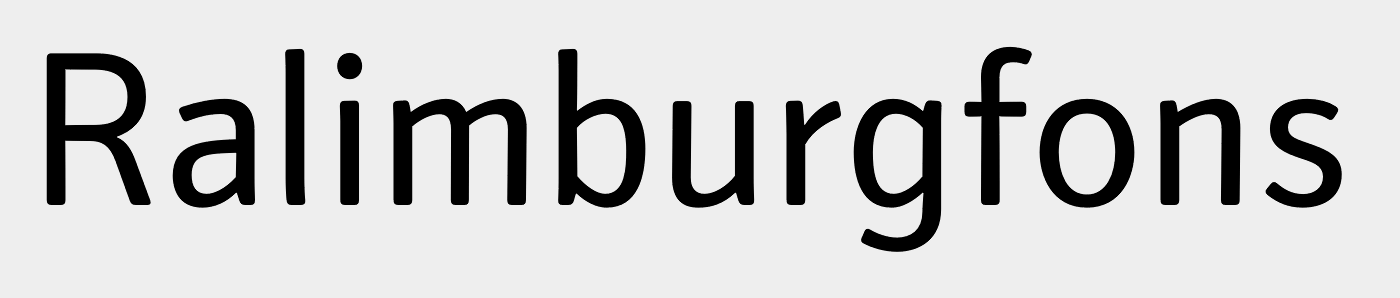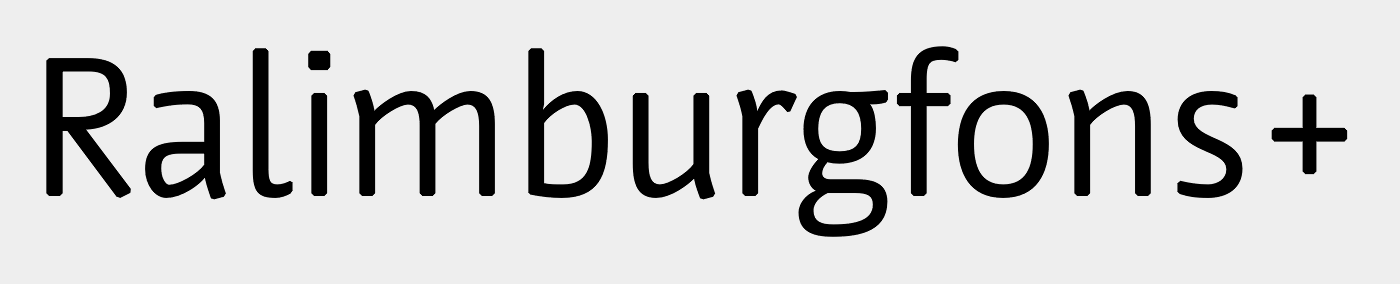
Schriften mit abgerundeten Ecken - Alternative zu Amsi Pro
Ich bin auf der Suche nach einer Schrift mit abgerundeten Ecken. Eigentlich gefällt mir Amsi Pro Bold sehr gut, aber die Schrift hat einige Tücken. Aufgrund der geringen Oberlänge verliert sie bei längeren Wörtern und Titeln mit vielen Wörtern schnell an Prägnanz und wirkt dann sehr gedrungen.
Kennt jemand eine gute Alternative? Die Schrift soll abgerundete bzw. gebrochene Ecken haben, ansonsten aber sehr klar und schnörkellos sein. Schriften wie die Berliner Groteske passen deshalb nicht. Und die Brandon Grotesque ist mir zu aufrecht, Panton zu rund und Brauer Neue zu eng.
Museo Sans Rounded 500, FF Unit Rounded und Secca Soft sind etwas gar rund.
Bei Manual Round gefallen mir r, g, b, n nicht.
Bei PTL Manual Round sind mir die Oberlängen zu lang.
Bei FF Nuvo Pro mag ich r nicht.
Antartida trifft es bisher am besten. Allerdings vermittelt die trotz Rundungen recht viel Technik.